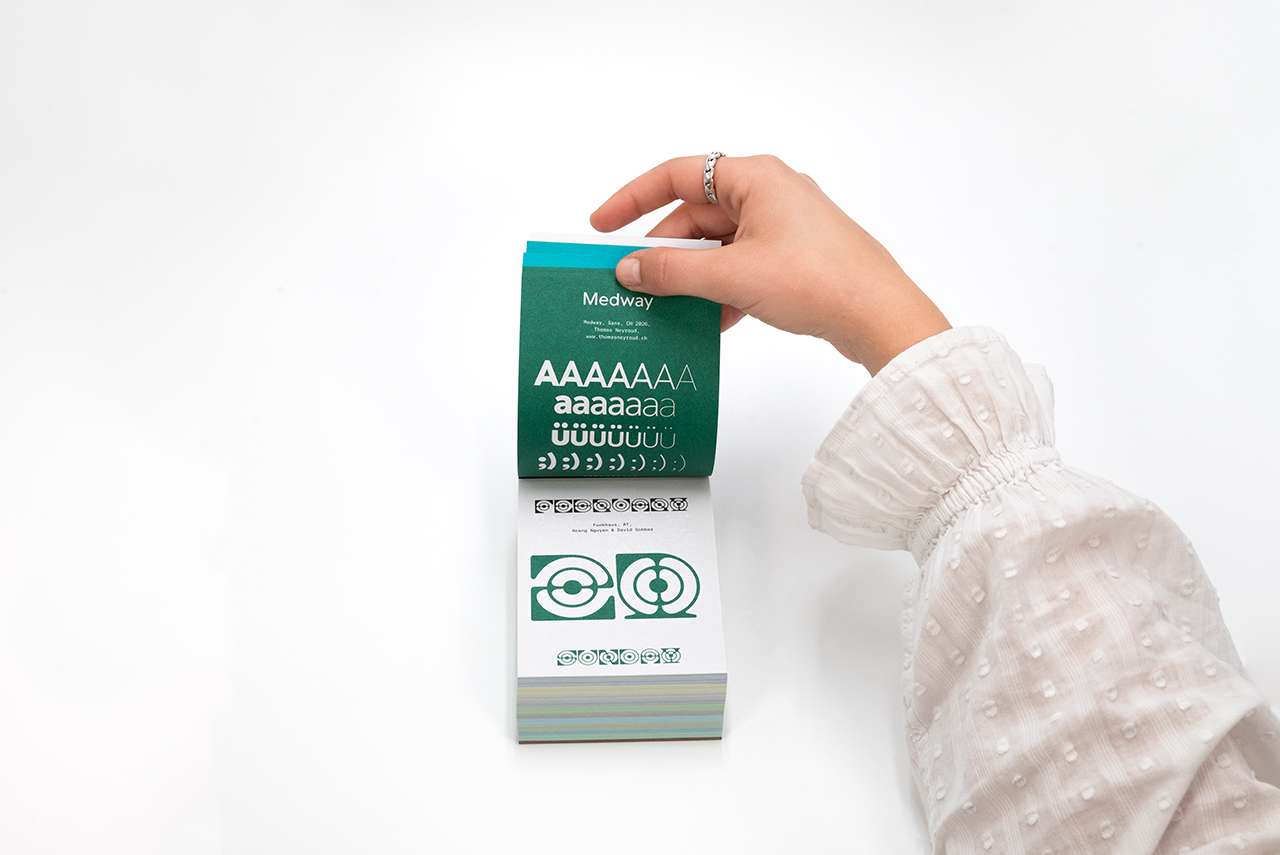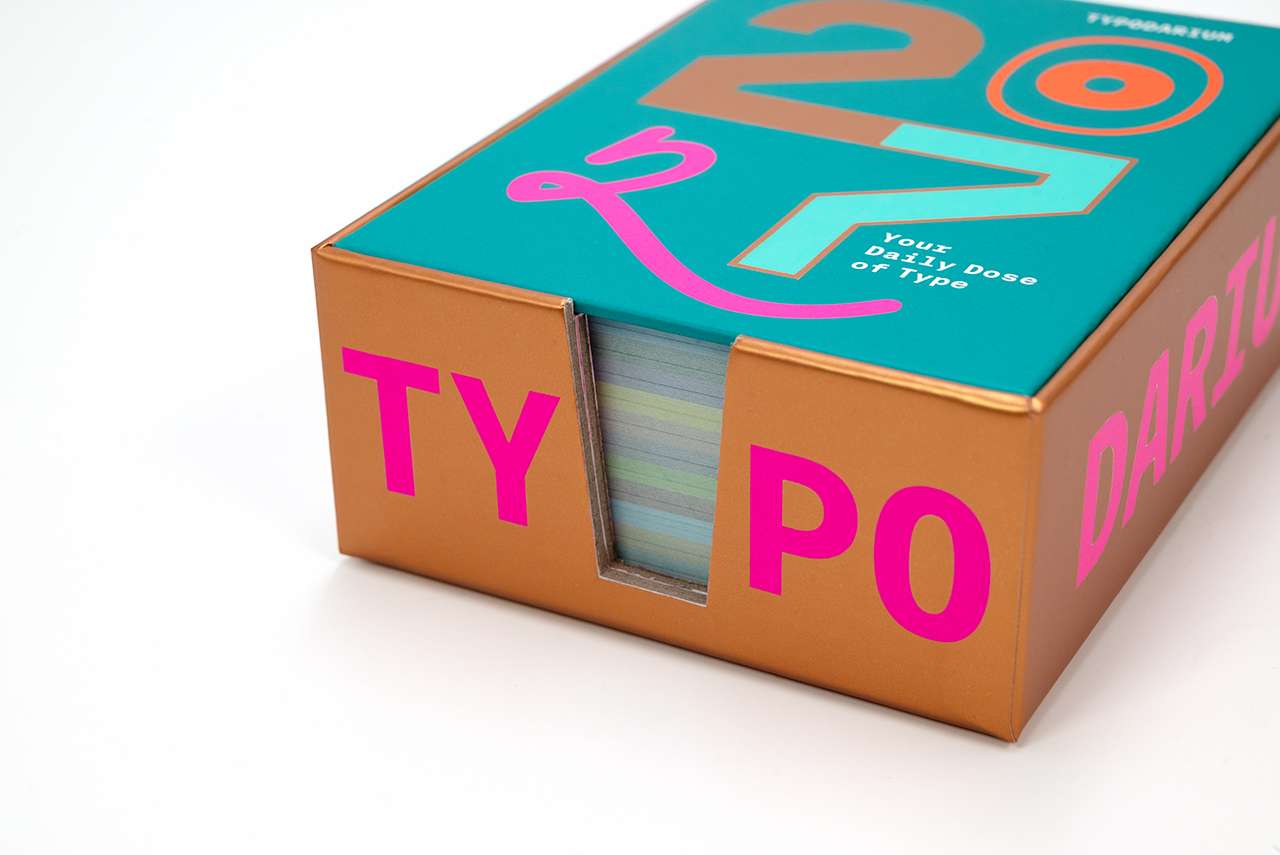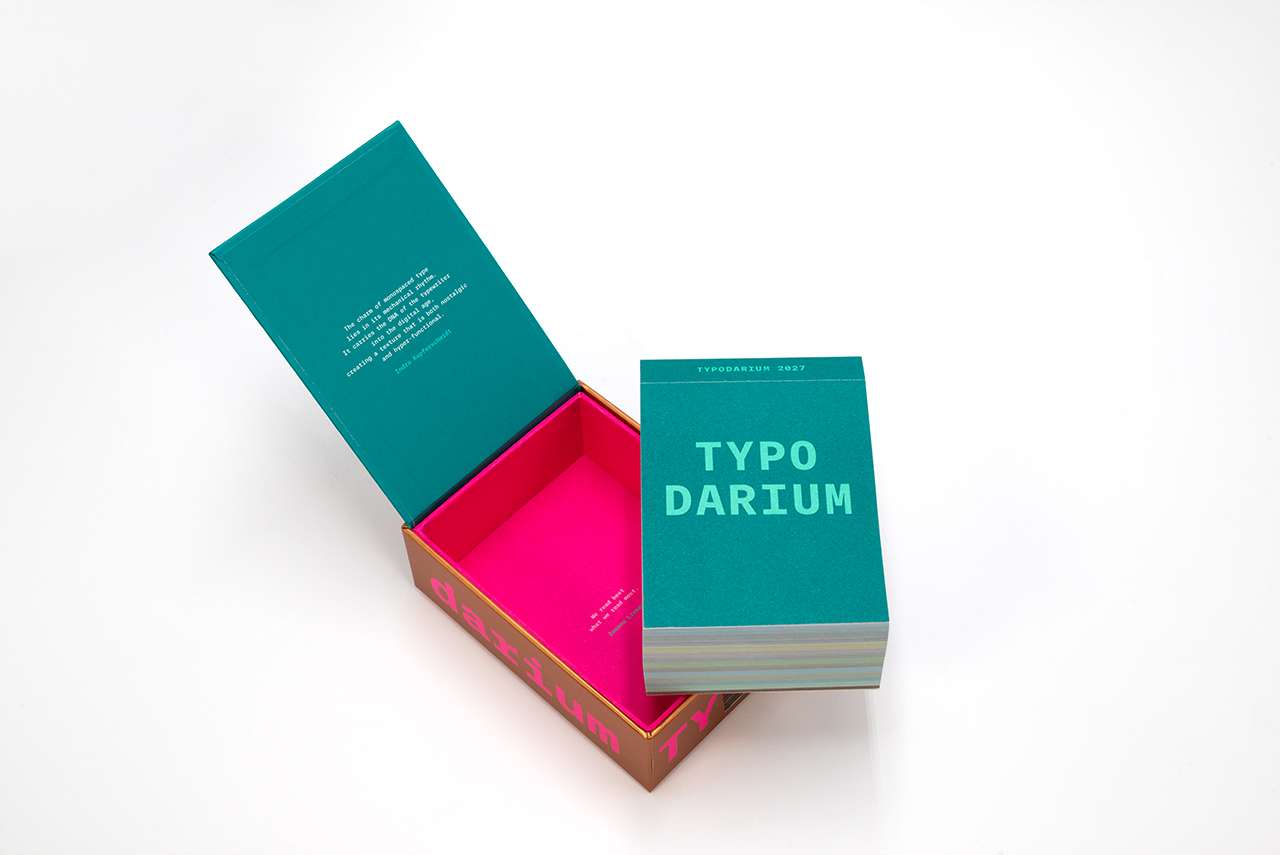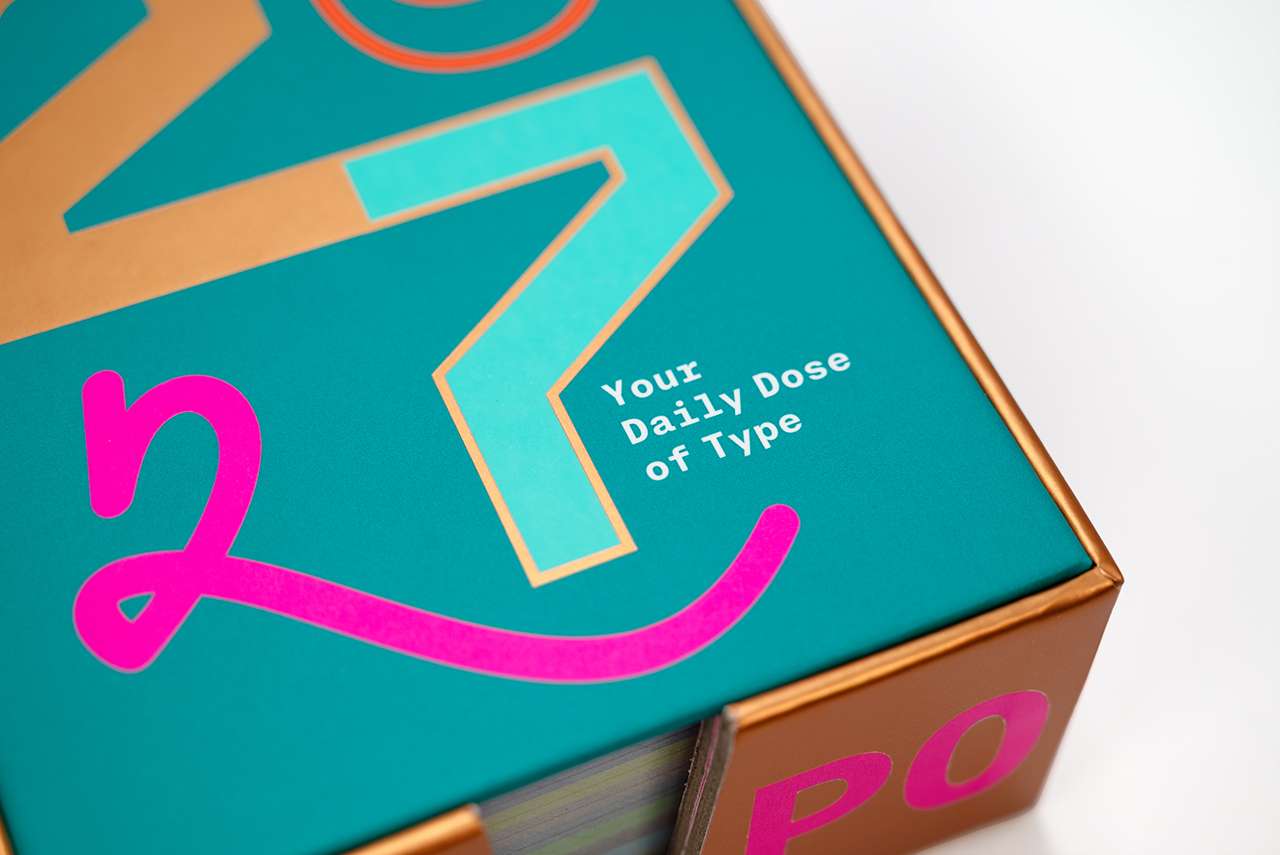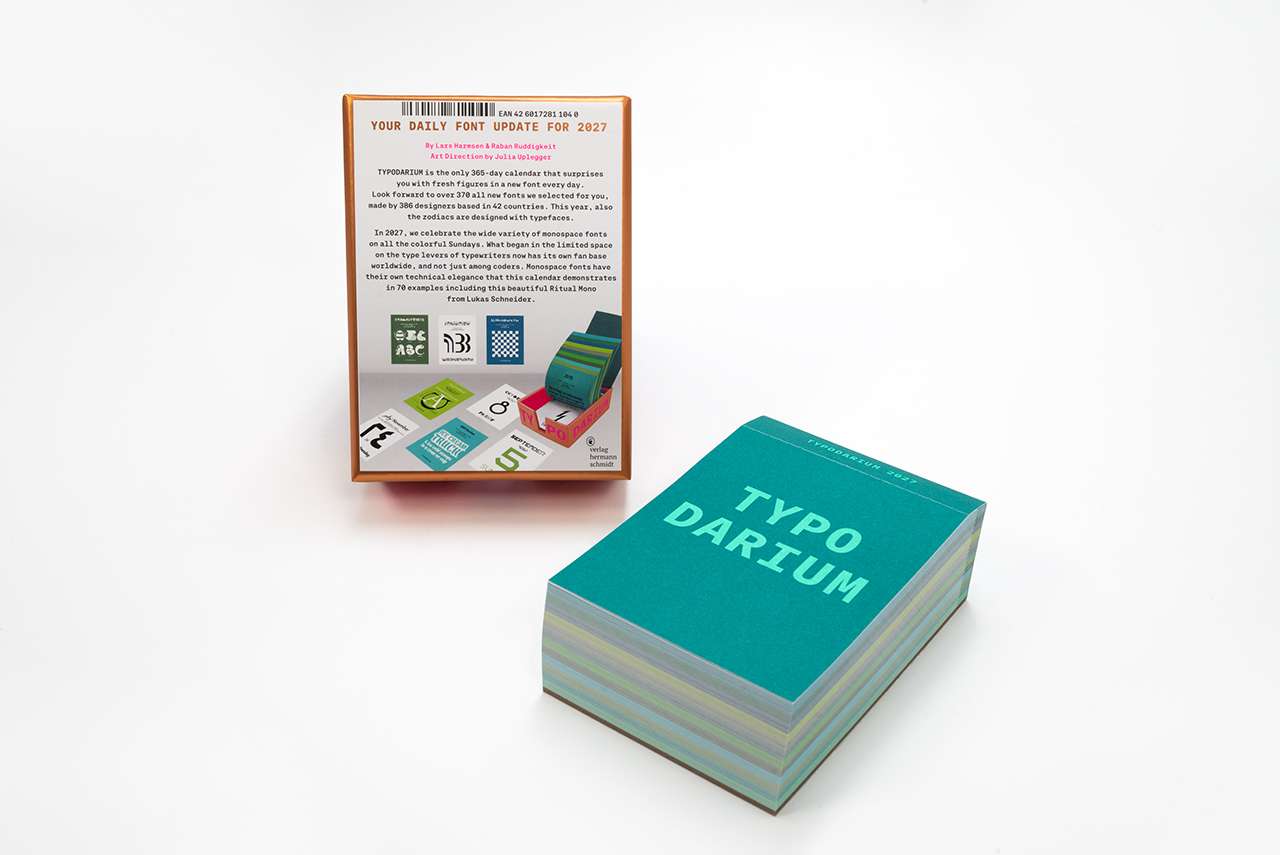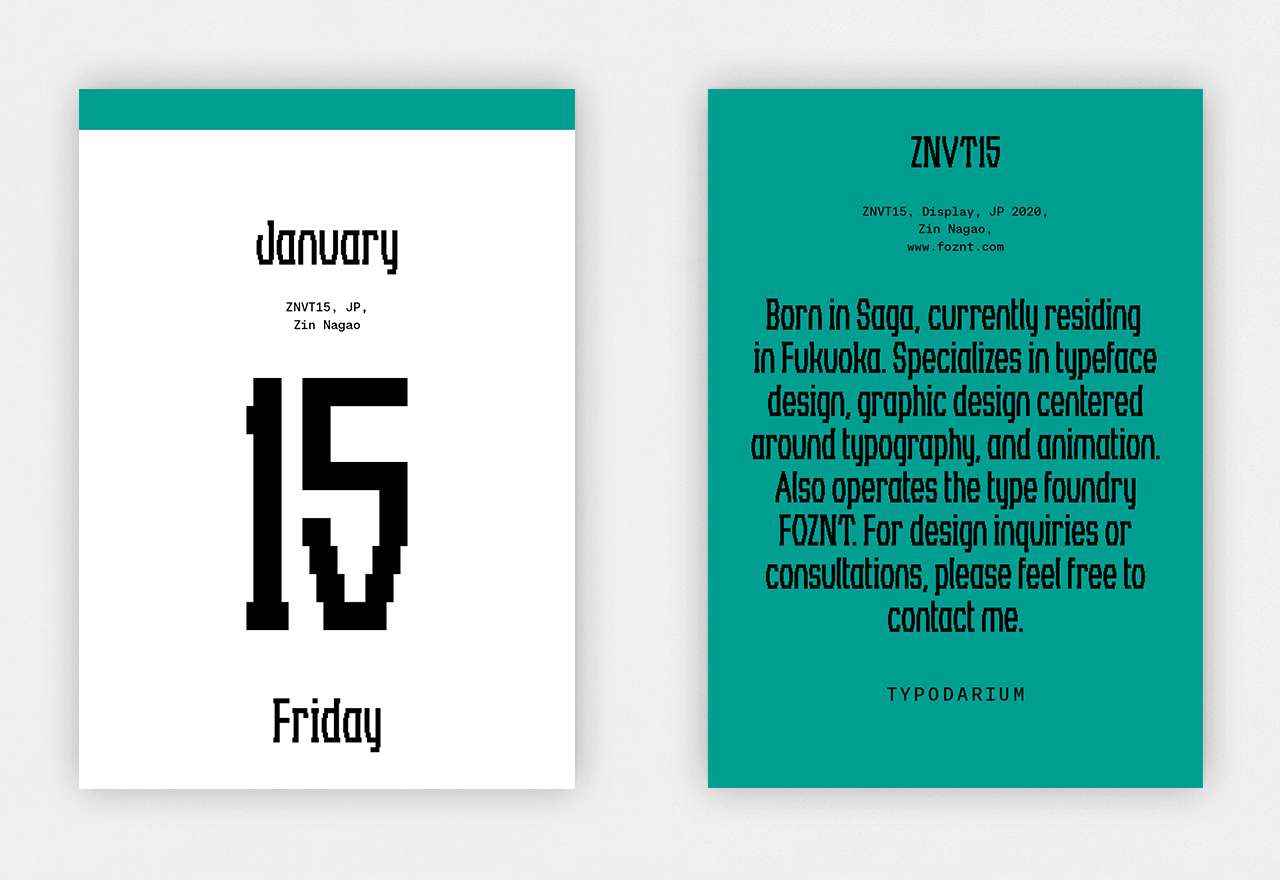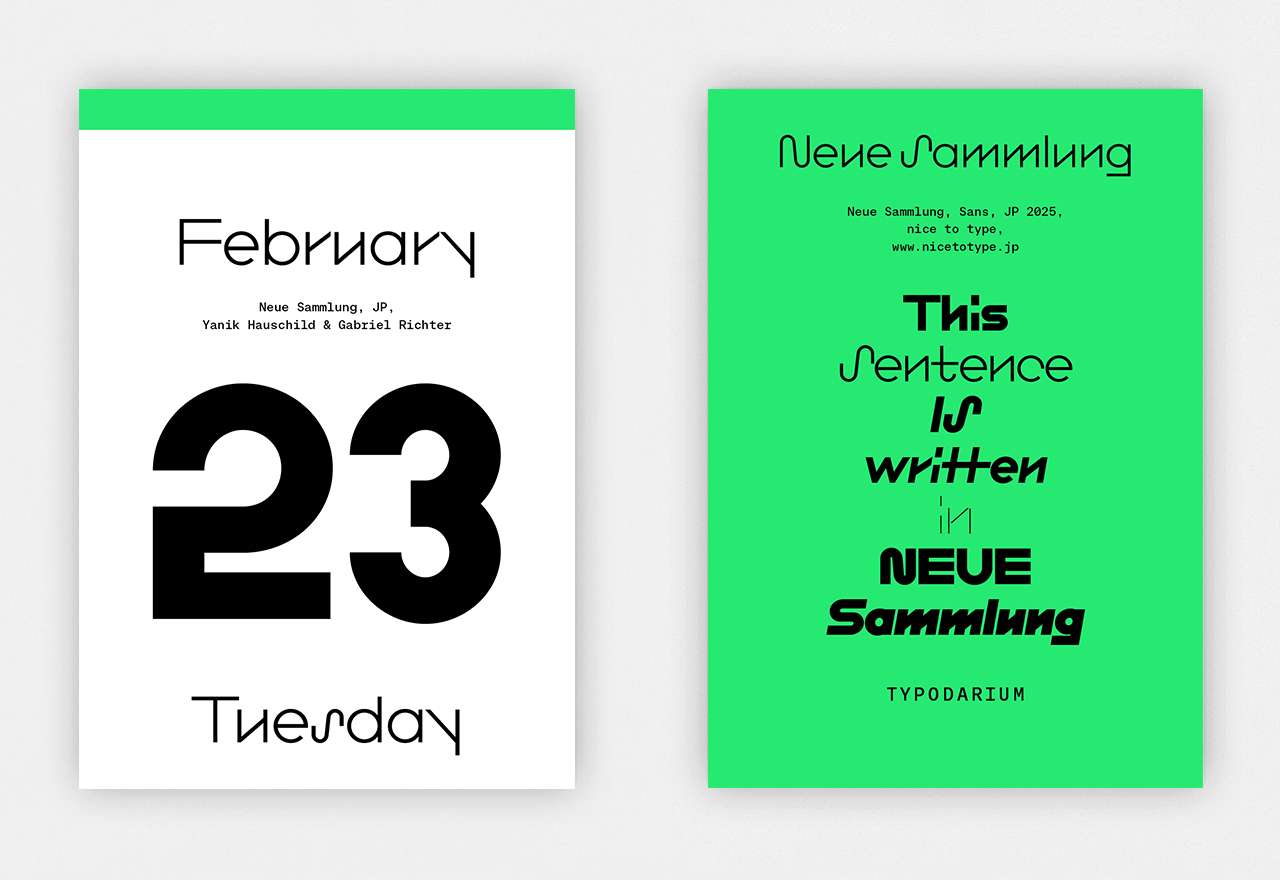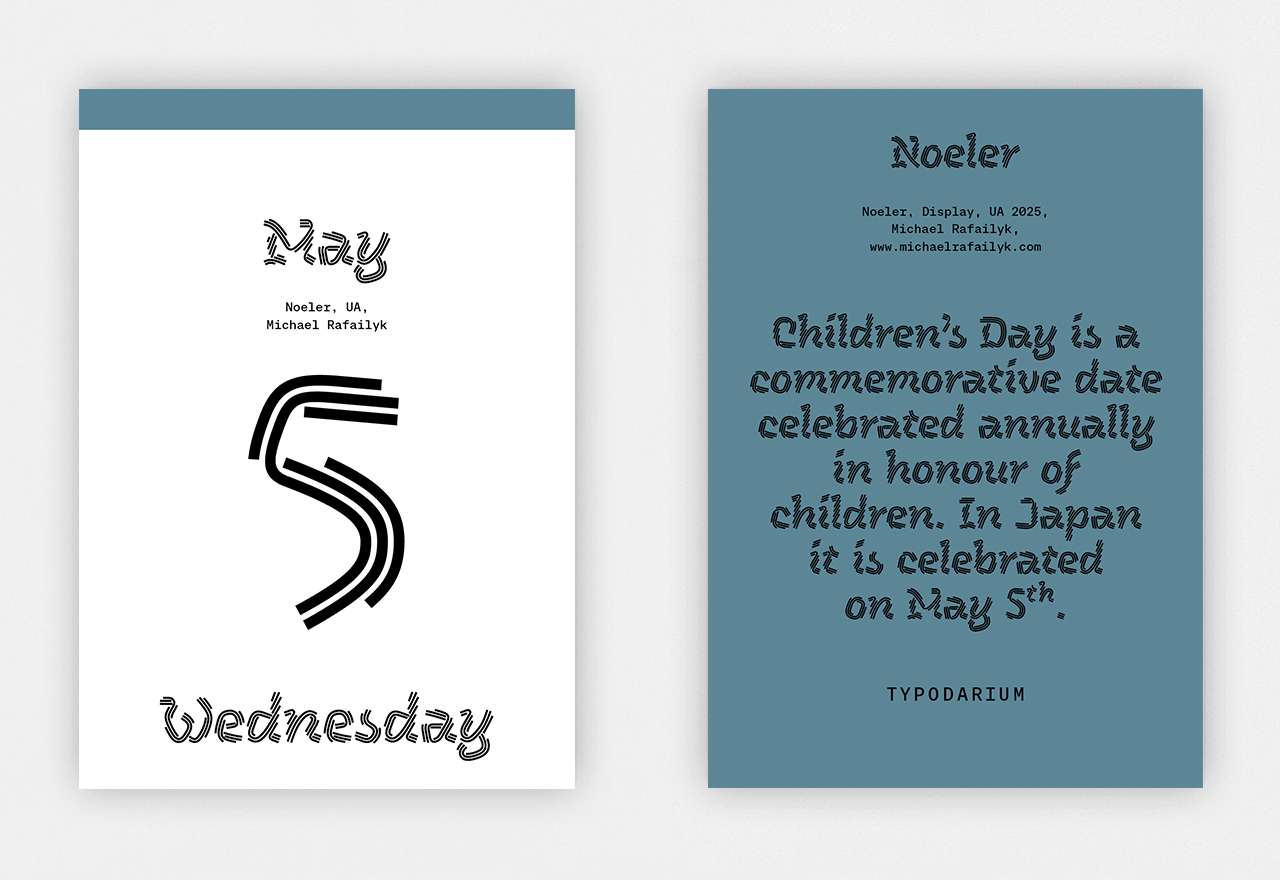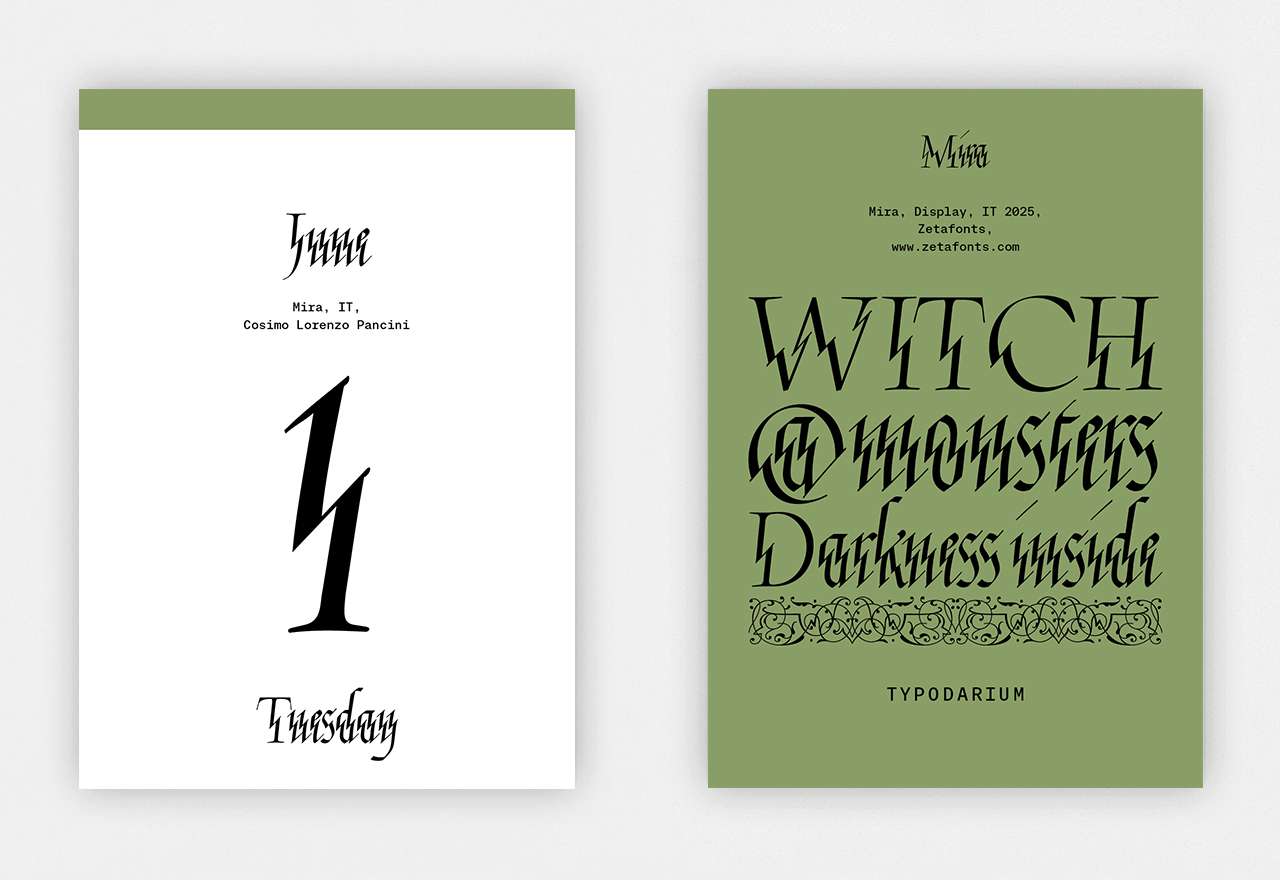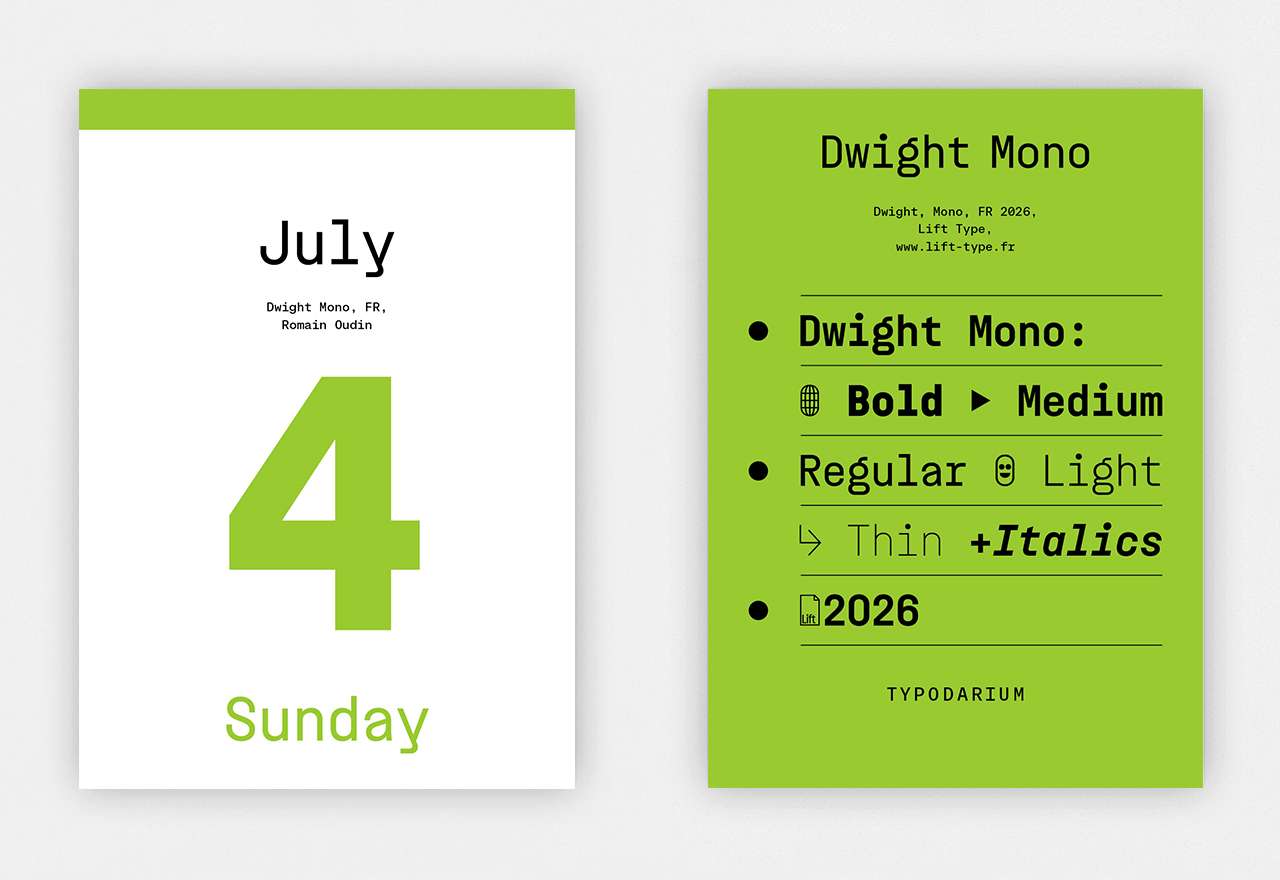
Trendradar Typedesign – oder: Warum Schriftgestaltung so wichtig ist
Die Wahl der passenden Schrift ist eine vielfach unterschätzte Komponente visueller Komposition. Typedesign wird von Lesenden oft nicht bewusst wahrgenommen. Es kommuniziert unterschwellig. Und powervoll.
Gute Gestalter:innen sind deshalb stets auf der Suche nach neuen Schriften, die Texten subtil Ausdruck verleihen und ihnen die heiß umkämpfte Aufmerksamkeit der Leser:innen sichern. Doch wo finden Sie neue Schriften? Wie orientieren Sie sich im Schriftendschungel? Wer scoutet für Sie die besten Typedesigner:innen und ihre aktuellen Entwürfe?
Julia Uplegger, Raban Ruddigkeit und Lars Harmsen kennen die internationale Type-Szene und begleiten sie seit vielen Jahren. Sie entdecken neue Talente und neue Schriften von »alten Hasen«. Sie sammeln und sortieren, analysieren und bewerten und stellen eine Auswahl zusammen, die nah am Trend ist und hoch in der Qualität. Und sie ersparen Ihnen damit die eigene Recherchearbeit. Das macht den Wert – und die Wertschätzung des Typodarium seit Jahren aus.
Das Typodarium hat sich als Impulsgeber im Typo-Geschehen etabliert und wird von Gestalter:innen und Agentur-Kreativen jährlich sehnsüchtig erwartet. Immer wieder sonntags überrascht es mit Meta-Trends. In 2027 zeichnen sich die Sonntage mit angesagten Monospace-Schriften aus: die Schreibmaschine erlebt auf Flohmärkten ein Revival und Type-Designer:innen aus aller Welt mixen Retro-Charme mit zeitgenössischer Ästhetik …
Wie das Typodarium zu uns kam
Als Raban Ruddigkeit uns vor einer halben Ewigkeit im Sommer von der Idee berichtete, einen Typedesign-Tagesabreißkalender zusammenzutragen, waren wir begeistert. Es war aber eben Sommer – und die Kalendersaison für den Handel war lange vorbei. Wir wussten das nicht – und als man es uns sagte, dachten wir »der Jahreswechsel ist ja noch lange hin«. Manchmal ist es gut, sich nicht an die ungeschriebenen Gesetze einer Branche zu halten! Das Typodarium erschien im Oktober – und trat einen Siegeszug an, weil es nicht nur Typo-Nerds, sondern daneben auch Menschen faszinierte, die sich der unendlichen Vielfalt an Schriften bis dato nicht so bewusst waren, sich aber dafür begeisterten.
Der Kalender bekam irgendwann eine Box, später farbige Rückseiten, er veränderte sich – und blieb sich treu. Er versammelte eine solide Fangemeinde um sich und ist heute aus dem Leben der Kreativen nicht wegzudenken. Das freut uns! Und stellt uns vor die Herausforderung, jedes Jahr eine neue Idee für die Sonntage zu entwickeln.
Zu Ausstattung und Gestaltung
Typodarium 2027
A 365 Day Type Calendar
Projektmanagement und Gestaltung: Julia Uplegger
Ein Tages-Abreißkalender mit 370 frischen Fonts
von 386 Designern und Foundries aus 42 Ländern
384 Tagesblätter in 12 fröhlichen Farben, beidseitig bedruckt
Format 8,5 x 12 cm
Verpackt in einer soliden, mit Bronzefarben veredelten Sammelbox in drei Sonderfarben gedruckt
So unterschätzt Schrift in der Visuellen Kommunikation ist, so entscheidend ist sie – und umwerfend vielfältig.